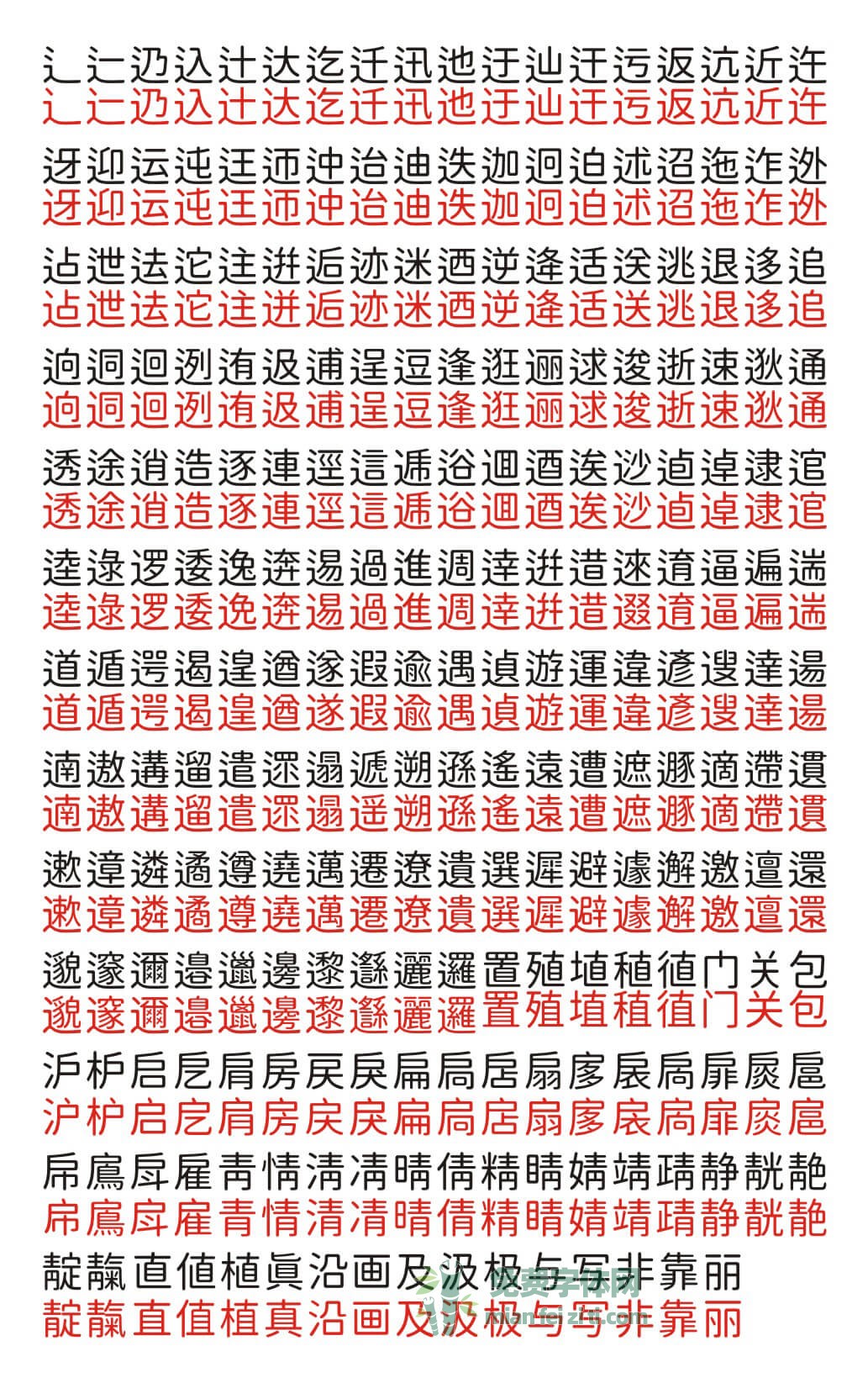
江城圆体-一款可以完全免费商用的适合设计师的字体合集
免费字体网之前一直觉得没有一款比较适合的可以免费商用的圆体字形。在搜集免费商用中文字体的过程中,发觉大部分的文章都介绍使用“思源柔黑体”,后来我发表了一篇文章《源柔黑体:日本自家製フォント工房改造的思源字体》为“思源柔黑体”正名。因为这款字体应该叫“源柔黑体”而不应该叫“思源柔黑体”,具体原因大家可以看一下源柔黑体那篇文章。
免费字体网那时建议大家使用源泉圆体或资源圆体替换掉网上一直流传的“思源柔黑体“,但是这两款字体对于中国大陆的设计师来说依然有点小瑕疵。源泉圆体因为是台湾设计师改造的字体,所以字形上会更贴近中国台湾的使用习惯。比如源泉圆体某些字的写法还是台版字形,而资源圆体则是思源黑体的直接变圆版,字形上保留着黑脚,看上去还是比较像黑体。
江城圆体改过的字